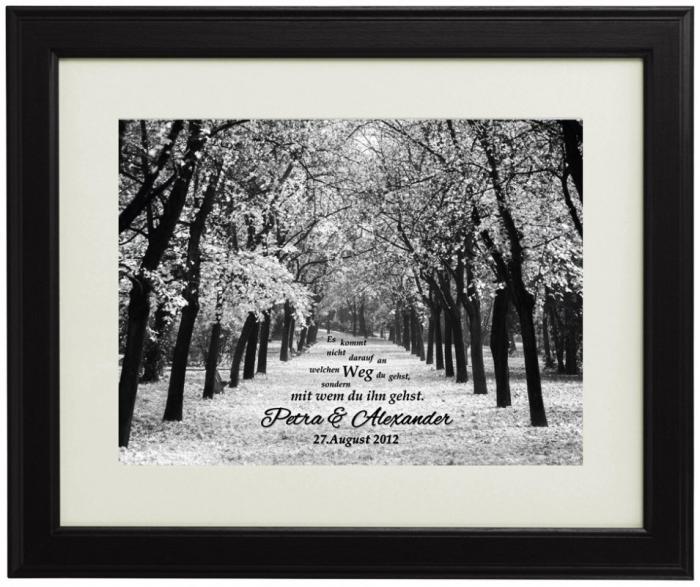
abgestufte Schrift
kann mir jemand sagen ob es eine solche Schriftart auf dem Bild (siehe Anhang) gibt.
Ich beziehe mich auf den oberen Teil. Ich wollte auch eine so abgestufte Schrift haben.
Wenn es diese nicht gibt, kann mir jemand evtl einen Typ geben, wie ich es sonst hinbekomme.
bei deinem Beispiel wurden einfach in einem Satz oder Grafikprogramm die Wörter bzw. Satzteile einzeln platziert und skaliert. Diesen "Effekt" kannst Du im schlimmsten Fall sogar mit PowerPoint erreichen.
Die Schriftart wird eine kursive Barock-Antiqua sein - genauer lässt sich das bei der geringen Auflösung nicht sagen.
... und Alexander ist die Alex Brush  :hammer:
Die Palatino ist eher eine Renaissance-Antiqua.